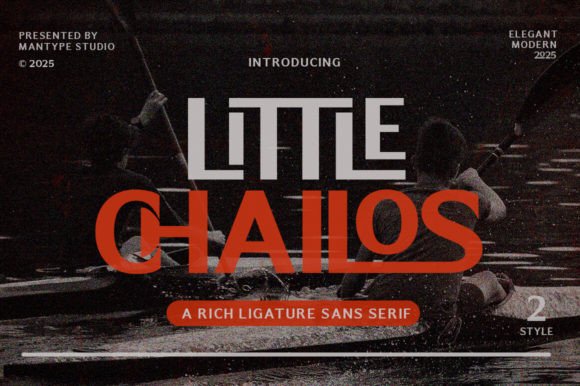
Little Chailos
Conçu avec précision, Little Chailos offre des vecteurs nets, une typographie fluide et une licence commerciale pour une tranquillité d'esprit.